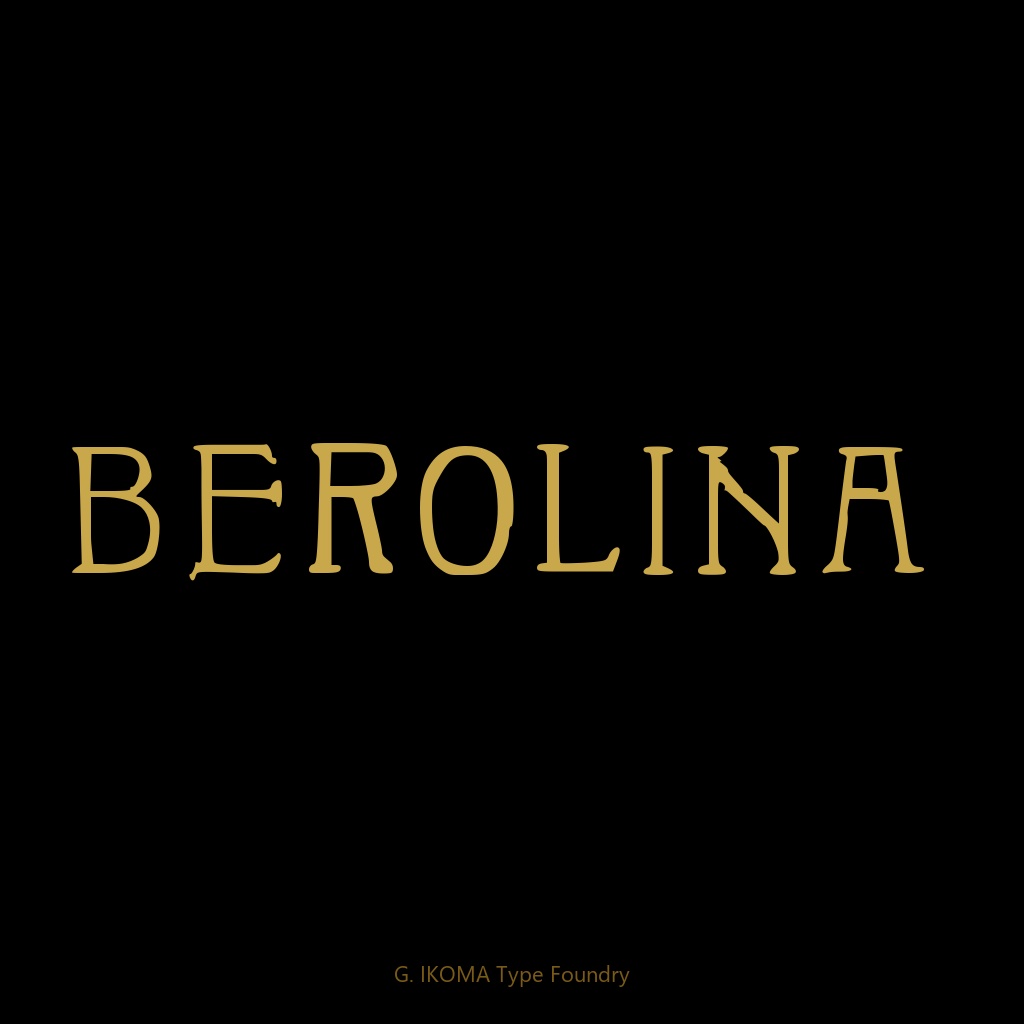
Berolina — 19世紀ベルリン活字復元フォント / Historical Revival Typeface [Condensed Serif · Berlin]
━━━━━━━━━━━━━━━━━━━━━━━━━━━━━━━━━━━ 【フォントについて】 ━━━━━━━━━━━━━━━━━━━━━━━━━━━━━━━━━━━ Berolina Extended は、19世紀末のベルリンを代表する活字鋳造所 W. Grönau's Schriftgiesserei(Berlin-Schöneberg)による書体を原典に、 手作業でトレース・デジタル化・拡張した復元フォントです。 凝縮された縦長のプロポーションと、均一なストローク、タイプライター的な 幾何学的整理感が特徴です。大文字・小文字・数字・記号を網羅しており、 ヴィンテージ印刷物、ポスター、パッケージ、ロゴ等に幅広く使用できます。 原典:W. Grönau's Schriftgiesserei, Berlin-Schöneberg(パブリックドメイン) 様式:Condensed Serif / Berlin Typeface 収録グリフ:92文字 欠落グリフ:'(アポストロフィ)、_(アンダースコア)の2文字 制作:株式会社生駒時計店 / G. IKOMA, LTD.(1870年創業) ━━━━━━━━━━━━━━━━━━━━━━━━━━━━━━━━━━━ 【収録内容】 ━━━━━━━━━━━━━━━━━━━━━━━━━━━━━━━━━━━ ・I_BEROLINA_Extended.ttf ・LICENSE.txt(日英) ━━━━━━━━━━━━━━━━━━━━━━━━━━━━━━━━━━━ 【ライセンス】 ━━━━━━━━━━━━━━━━━━━━━━━━━━━━━━━━━━━ 個人・商用利用可。印刷物・ロゴ・画像・動画サムネイル等に使用可能。 禁止:再配布・再販売・Webフォント設置・アプリ埋め込み・AI学習利用。 詳細は同梱 LICENSE.txt 参照。 ━━━━━━━━━━━━━━━━━━━━━━━━━━━━━━━━━━━ 【関連リンク】 ━━━━━━━━━━━━━━━━━━━━━━━━━━━━━━━━━━━ G. IKOMA Archive: https://g-ikoma-archive.netlify.app/ BOOTH: https://g-ikoma.booth.pm/